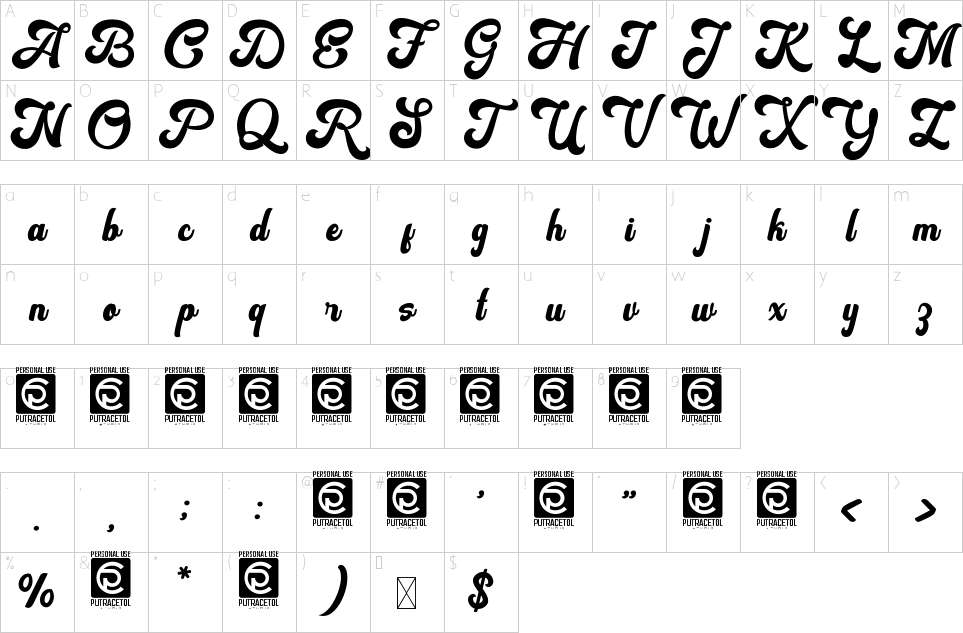
A fonte Vintage Party é uma escolha ideal para criar eventos memoráveis e cheios de estilo, seja para decoração de festas temáticas ou criações digitais que exalam um ar vintage. Desenvolvida por Putra Novembria Candra Kusuma, essa fonte se destaca pela sua elegância, tornando-a perfeita para celebrar ocasiões especiais com um toque nostálgico e divertido. Com 47.374 downloads confirmados desde seu lançamento, Vintage Party já foi adotada por designers de festas em todo o mundo como uma maneira criativa de transmitir a essência de uma celebração que nunca esgota seu encanto. Seja você quem está organizando um casamento, um aniversário ou até mesmo uma ceia para adultos mais velhos, Vintage Party oferece o elemento gráfico perfeito para transformar qualquer evento em um momento memorable e inesquecível.